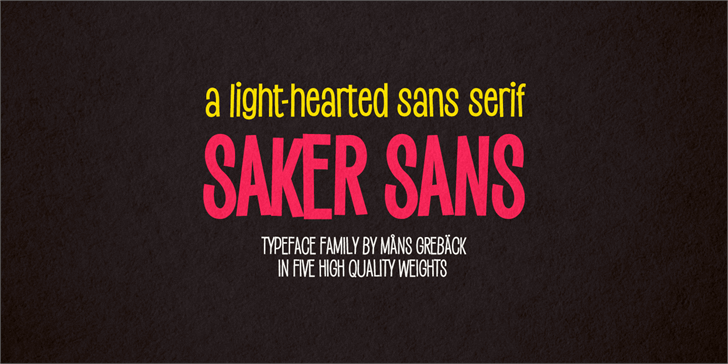
Saker Sans Light Font – Fonte Grátis
Saker Sans Light Font
Saker Sans Light é uma elegante fonte sans-serif que se destaca pelo seu equilibrado contraste de linhas e traços finos, criando um visual moderno e sofisticado para qualquer projeto. Desenvolvida pelo designer Måns Grebäck, essa fonte oferece um conjunto de linhas cuidadosamente balanceadas, que vão desde os detalhes mais sutis até as formas mais robustas. Ideal tanto para títulos como para texto corpo, ela ajuda a destacar seu design em qualquer página ou mídia digital. Para aqueles interessados em licenças comerciais, Måns Grebäck oferece uma variedade de opções através do site específico da fonte. Para perguntas mais específicas, há um FAQ disponível para consulta. Também pode se conectar diretamente com o criador por meio de sua página pessoal ou Facebook oficial. Com Saker Sans Light, você tem a garantia de uma fonte de qualidade que vai complementar suas criações de forma única e inovadora. Esta descrição é informativa e orientada para designers gráficos, equilibrando informações importantes sobre as características da fonte, onde encontrar mais detalhes e como entrar em contato com o designer.
Designer: Måns Grebäck